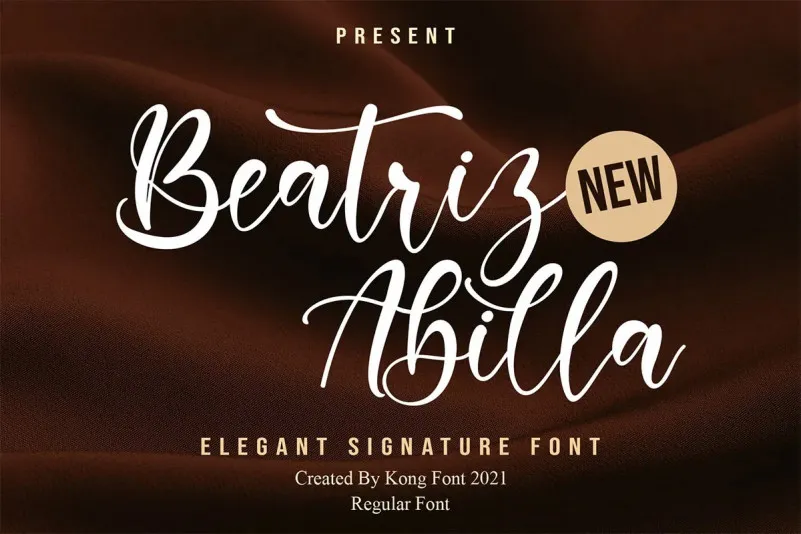
A fonte “Beatriz Abilla” é uma opção elegante e criativa para quem busca um estilo artesanal moderno. Desenvolvida pela Kong Font, ela oferece um conjunto completo de caracteres que vai do aprimorado ao minimalista. Perfeita para uso em cartões de aniversário, design de embalagens, identidade da marca, design manual e projetos DIY, o título de livros, convites de casamento, embalagens e muito mais. Composta por letras maiúsculas, minúsculas, números, símbolos, pontuação e ligaduras, esta fonte é um recurso valioso para designers profissionais e amadores em busca de uma solução versátil. Suas linhas fluidas e acentos sutis criam textura e personalidade, tornando-a ideal não apenas para projetos digitais, mas também para trabalho gráfico impresso. Adotar “Beatriz Abilla” no seu próximo projeto pode significar tanto para o design visual quanto para os seus clientes ou público. É uma escolha que reflete elegância contemporânea em cada detalhe de sua obra.